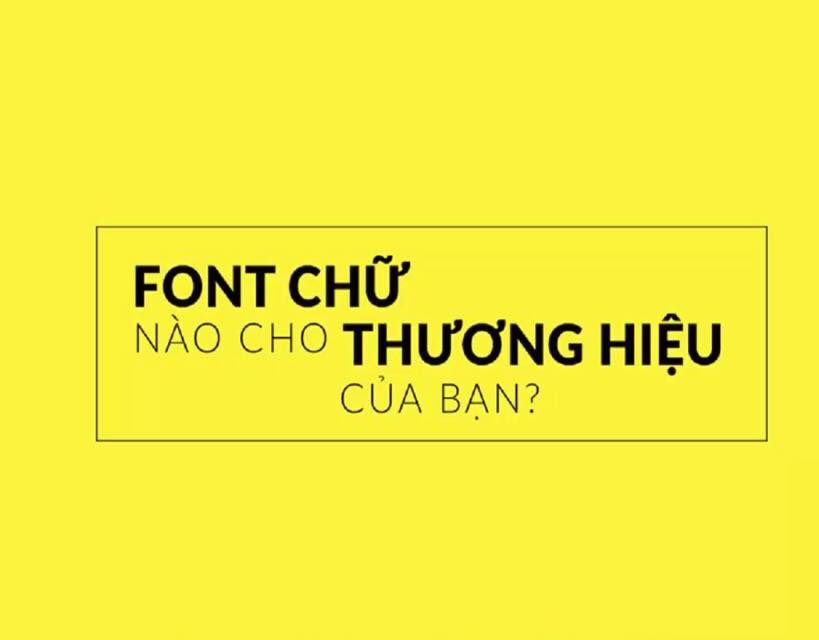
Font Chữ Thiết Kế
Top 10 font chữ việt hóa đẹp dùng cho thiết kế sản phẩm font hapna hapna là loại font slab serif hình học có bản chất vô cùng khác biệt với những font slab serif khác đang có trên thị trường.
Font chữ thiết kế. Hướng dẫn cơ bản về cách sử dụng thẻ div trong thiết kế giao diện web 19 859 lượt xem. Font chữ này là lựa chọn tuyệt vời cho các bảng hiệu lớn tiêu đề nhãn hàng tựa báo và nhiều định dạng thiết kế đồ họa trực tuyến khác. The circus display 3. Hôm nay mình sẽ giới thiệu một vài mẫu font tiếng việt đẹp được.
Font chữ đẹp dành cho thiết kế. 10 font chữ an toàn nhất trong thiết kế website 71 387 lượt xem html html5 phần 24. 26 bộ font chữ tattoo độc đáo và rất hầm hố 24 05 2012. Bạn chỉ cần download mà không phải mất thời gian để chọn lọc.
Chúng tôi sẽ giới thiệu cho bạn bộ danh sách hơn 1 000 font chữ đẹp đã được chọn lọc. Bạn muốn tìm kiếm font chữ đẹp để thiết kế website thiết kế các sản phẩm in ấn. Vai trò của các font chữ thiết kế logo là vô cùng quan trọng. 30 font chữ hoa dành cho những thiết kế đáng yêu.
Sau đây là một số font chữ tuyệt vời đa dạng phong cách mà idesign đã tổng hợp hy vọng chúng có thể giúp bạn tạo nên những tác phẩm tuyệt vời. Ngoài ra thì poiret cũng có thể được sử dụng cho animation in áo thun logo và áp phích. 69 font chữ thiết kế logo ấn tượng kèm link download. 40 font chữ vintage dành cho những thiết kế cổ điển.
Mỗi font chữ trong bộ font full đều có những đặc trưng rất riêng không chỉ là các font chữ cơ bản mà rất nhiều font chữ nghệ thuật dành riêng cho dân thiết kế thỏa sức sáng tạo cho bản vẽ của mình. Font chữ phải lột tả được tính chất cảm xúc cũng như thông điệp mà công ty doanh nghiệp muốn truyền tải đến khách hàng của mình. Một số template bootstrap miễn phí đẹp và tuyệt. 60 font chữ tốt nhất cho thiết kế logo 28 font chữ hoa miễn phí cho dân thiết kế share bộ 214 font unicode vn đẹp cho thiết kế.